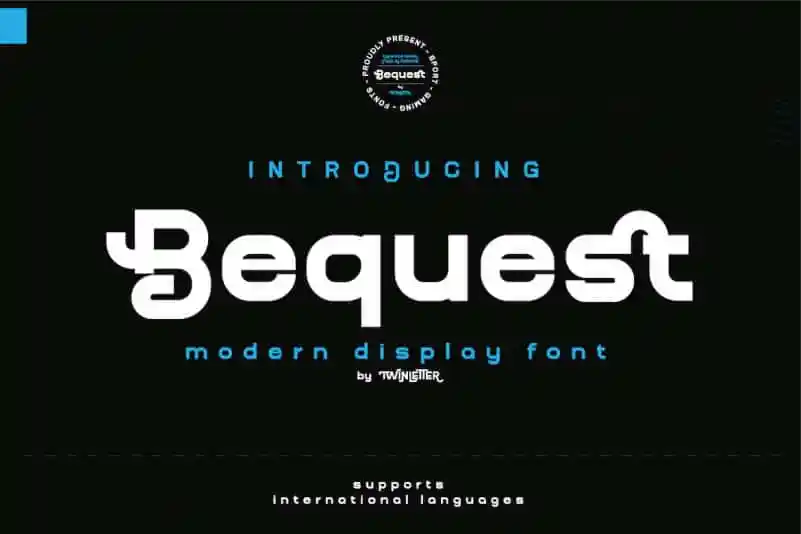
Bequest Sans Serif Font Family – Download Grátis
A Bequest Sans Serif Font é uma escolha perfeita para diversos projetos que exigem uma aparência limpa e moderna. Essencialmente, essa fonte atende a um amplo espectro de aplicabilidades, desde os jogos e eventos esportivos até as marcas de logotipo e postagens nas mídias sociais. Também é indicada para banners, fitas, materiais promocionais de alimentos e bebidas, títulos de filmes e tecnologia. Com uma família complementar gratuita para cabeçalhos, subtítulos e texto em fluxo natural, você pode garantir que todas as suas criações de design sejam inovadoras e únicas. Mas o verdadeiro valor dessa fonte reside em sua familia complementar gratuita. Essa opção oferece a vantagem adicional de personalizar ainda mais seus designs, criando um visual consistente ou diferenciado conforme necessário. Como uma fonte demo gratuitamente disponível para uso pessoal, você tem liberdade para experimentá-la antes de investir em um contrato comercial. As doações não são necessárias, mas muito apreciadas por contribuir com o desenvolvimento contínuo desta família de fontes. A Bequest Sans Serif é uma adição invaluable a qualquer designer ou criador que busca estilizar seus projetos de maneira eficaz e elegante.